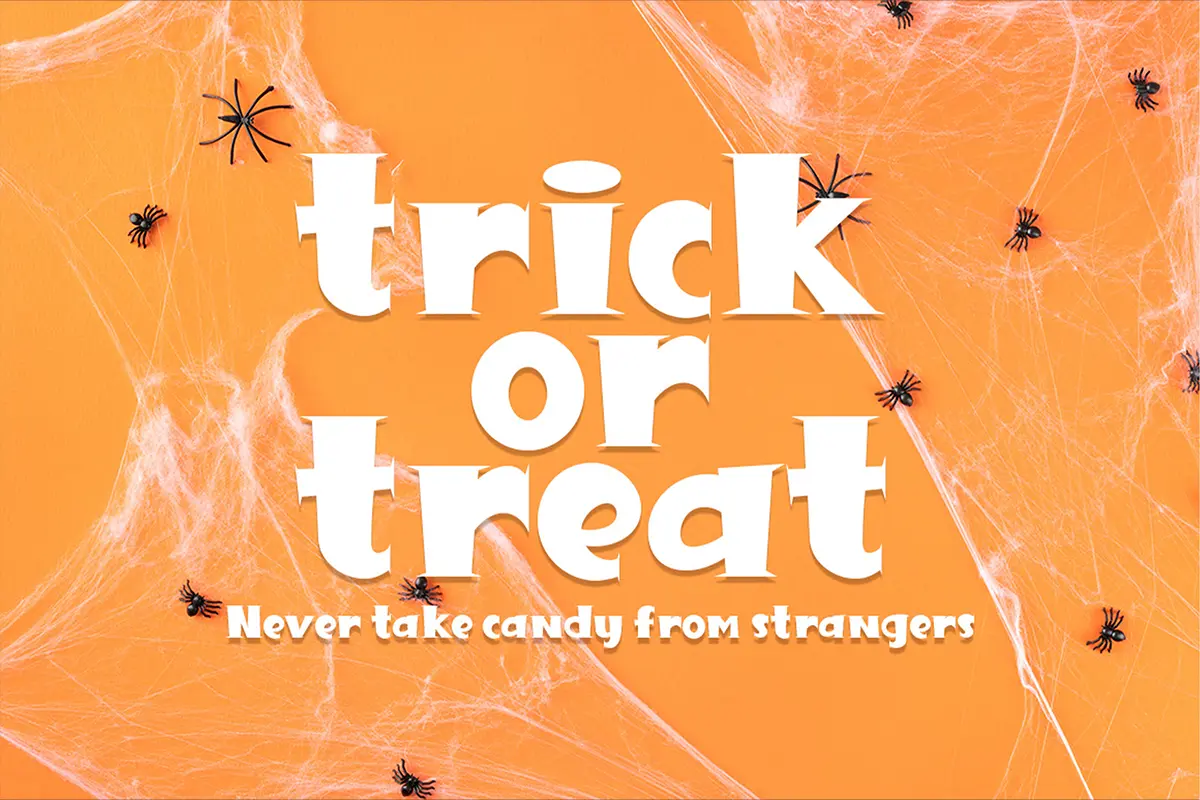
فونت فانتزی و ترسناک هیولا
Great Monster یک فونت نمایشی جذاب، جسور و فانکی است که حالوهوای هالووینی و فانتزی را به هر طراحی اضافه میکند. این فونت با استایل بازیگوش و انرژی بالایی که دارد، هر پروژهای را زنده و چشمگیر میکند—از پوسترهای هالووین گرفته تا کارت دعوت، استیکر، بستهبندی، طراحی تیشرت و پروژههای سرگرمکننده.
تنها محدودیت این فونت تخیل شماست؛ هر جا نیاز به یک تایپوگرافی پرهیجان و متفاوت دارید، Great Monster بهترین انتخاب است.
⭐ ویژگیهای محصول
- فونت نمایشی بولد و فانکی
- مناسب برای طراحیهای هالووینی، فانتزی و سرگرمی
- ایدهآل برای پوستر، کارت دعوت، استیکر، بستهبندی، تیشرت و پروژههای کودکانه
- شخصیت بصری شاد، جسور و پرانرژی
- مناسب برای پروژههای دیجیتال و چاپی